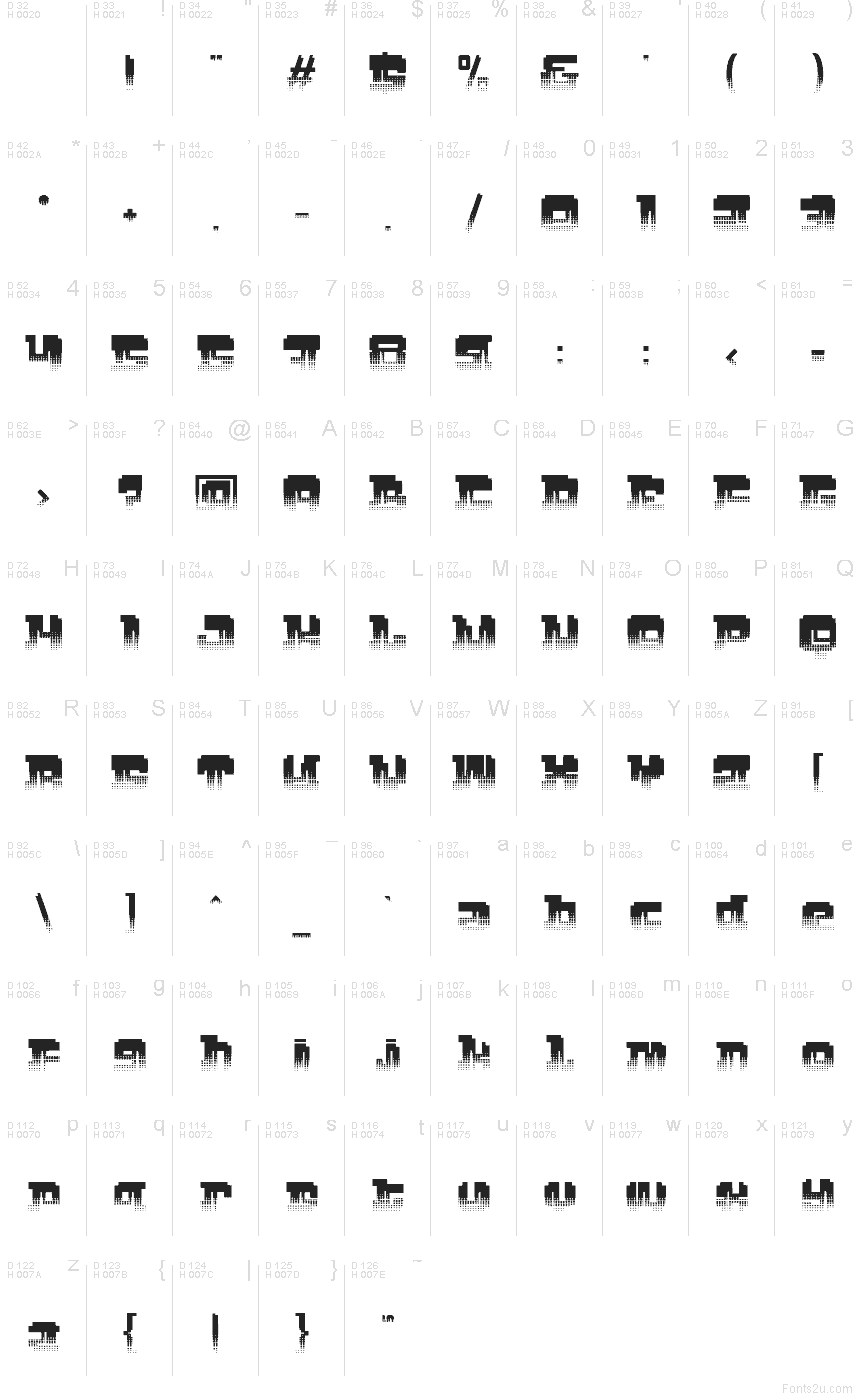
Techno Wave Five od Putracetol Studio je bezplatné futuristické písmo typu display, vytvořené z tvrdých, blokových tvarů, které se rozpadají do visících řad čtvercových bodů. Tato opakující se, v horní části masivní silueta dodává písmenům efekt digitálního rozkladu, jako by se tuhé techno formy rozpouštěly skrze mřížku.
Písmo nejlépe vynikne v názvech her, na sci-fi plakátech, v grafice pro hudební akce, na bannerech streamerů a úvodních obrazovkách, kde textura padajících pixelů skutečně podpoří vizuální dojem. Skvěle poslouží i pro krátká loga a záhlaví na sociálních sítích, protože přísná horní část a tečkovaný sestup vytvářejí efekt glitch, aniž by design působil jako čistý šum.